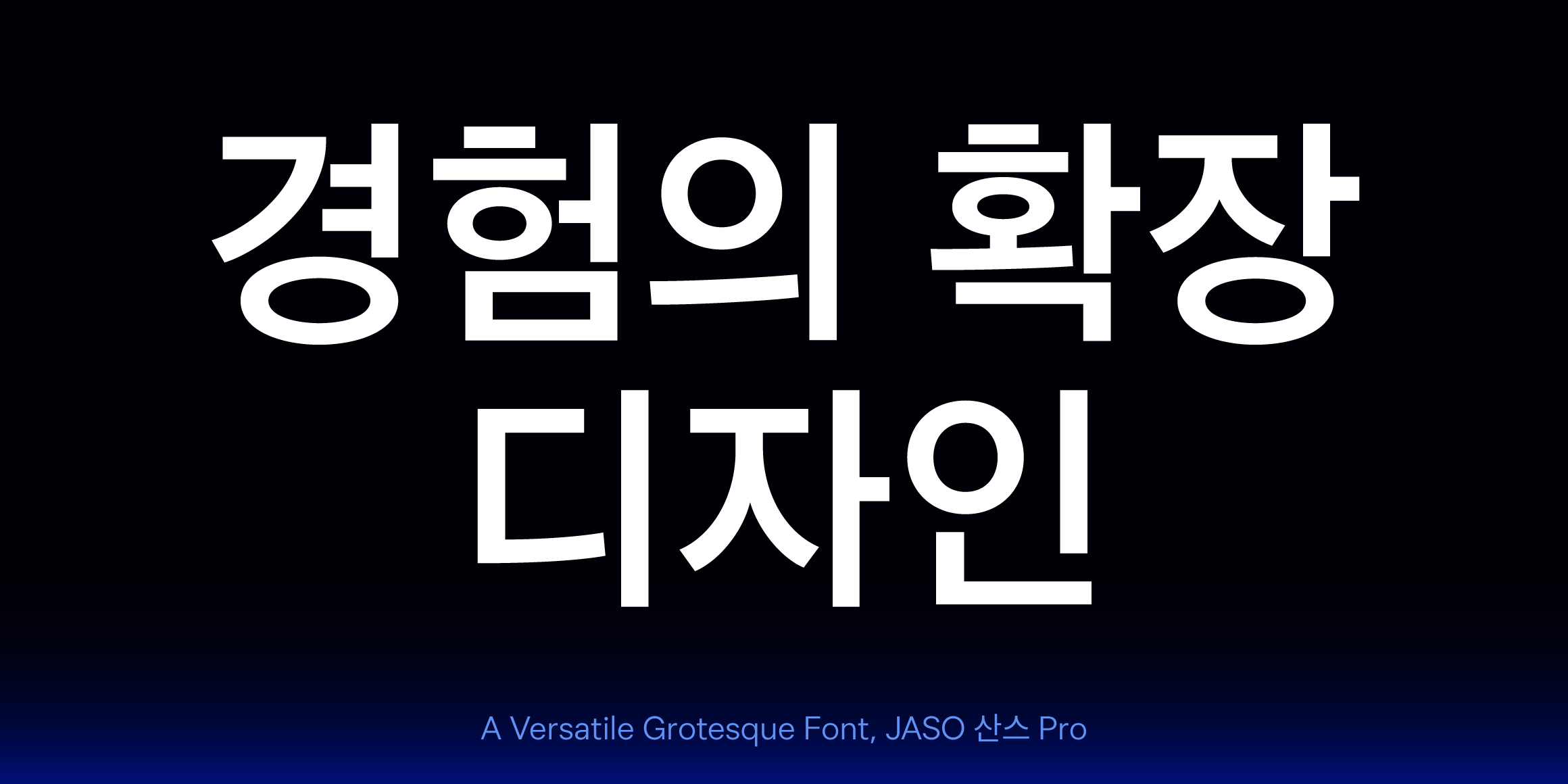
자음의 곡선 곡률을 보다 일반적인 수준으로 조정해, 기존 JASO 산스보다 한층 중립적인 인상으로 다듬었습니다. 반면 모음의 길이를 짧게 설계해 전체 실루엣이 네모틀에 맞아 보이는 기존의 특징은 그대로 유지했습니다.
덕분에 완전히 중립적이기보다는 은은한 명랑함이 남아 있으며, 한글과 영문을 함께 조합하거나 프레임 안에 한글을 배치할 때도 시각적으로 깔끔하게 정렬된 인상을 줍니다.
또한 각 웨이트마다 약 8,000자의 글리프를 추가해 JASO 산스 Pro에서는 한글 완성형 11,172자를 모두 지원합니다.
- JASO 산스 Pro / JASO Sans Pro